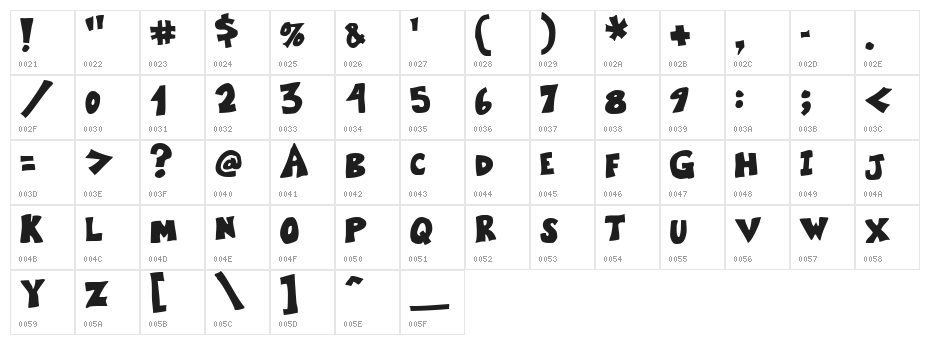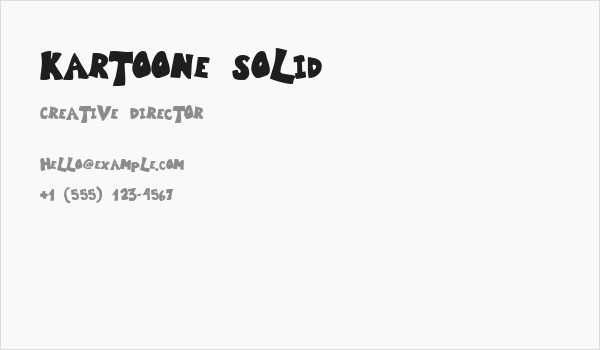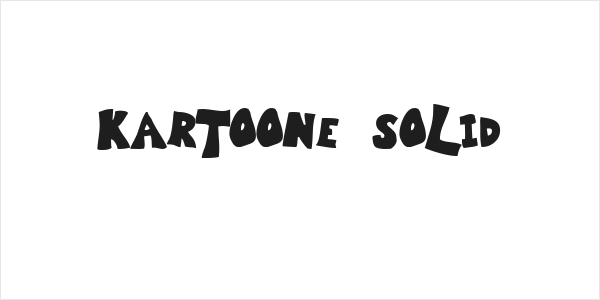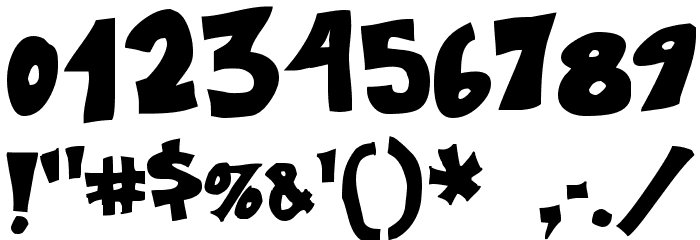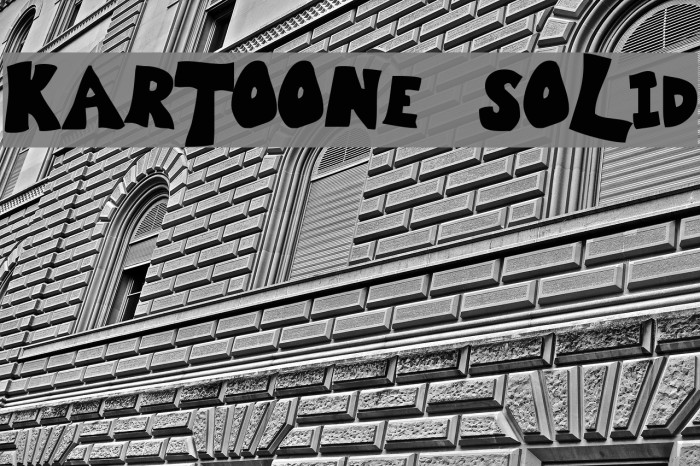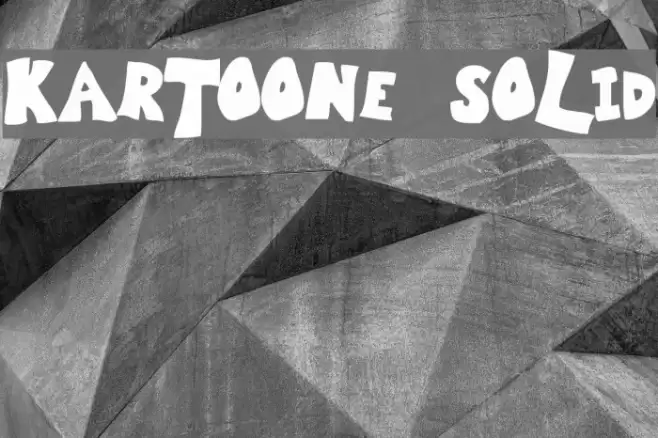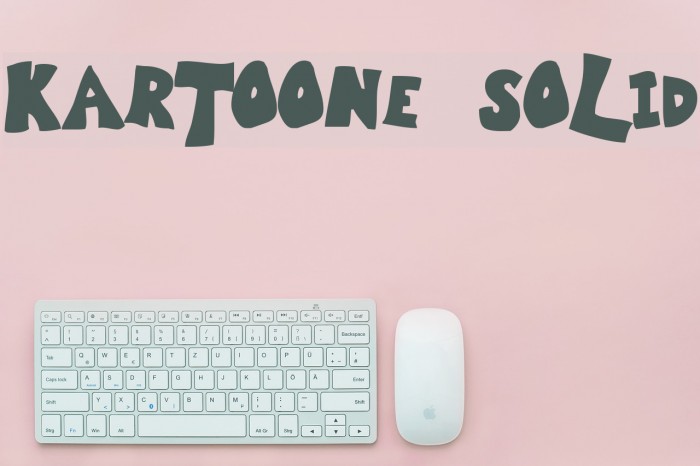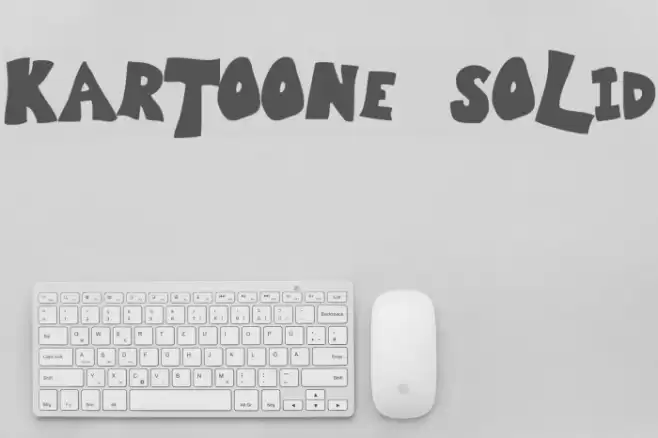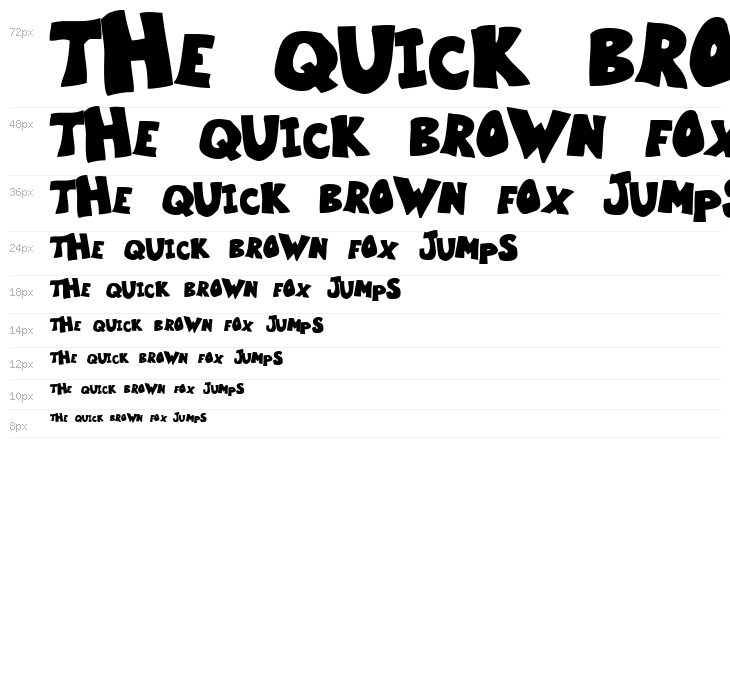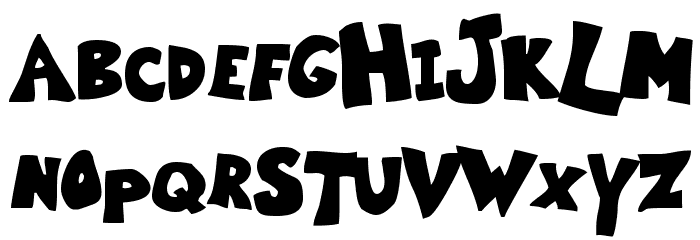
Kartoone Solid Font
| Gesamtstil | Playful, Cartoonish |
| Vorgeschlagene Projekte | Ideal for children's books, comic strips, playful branding, and informal posters. |